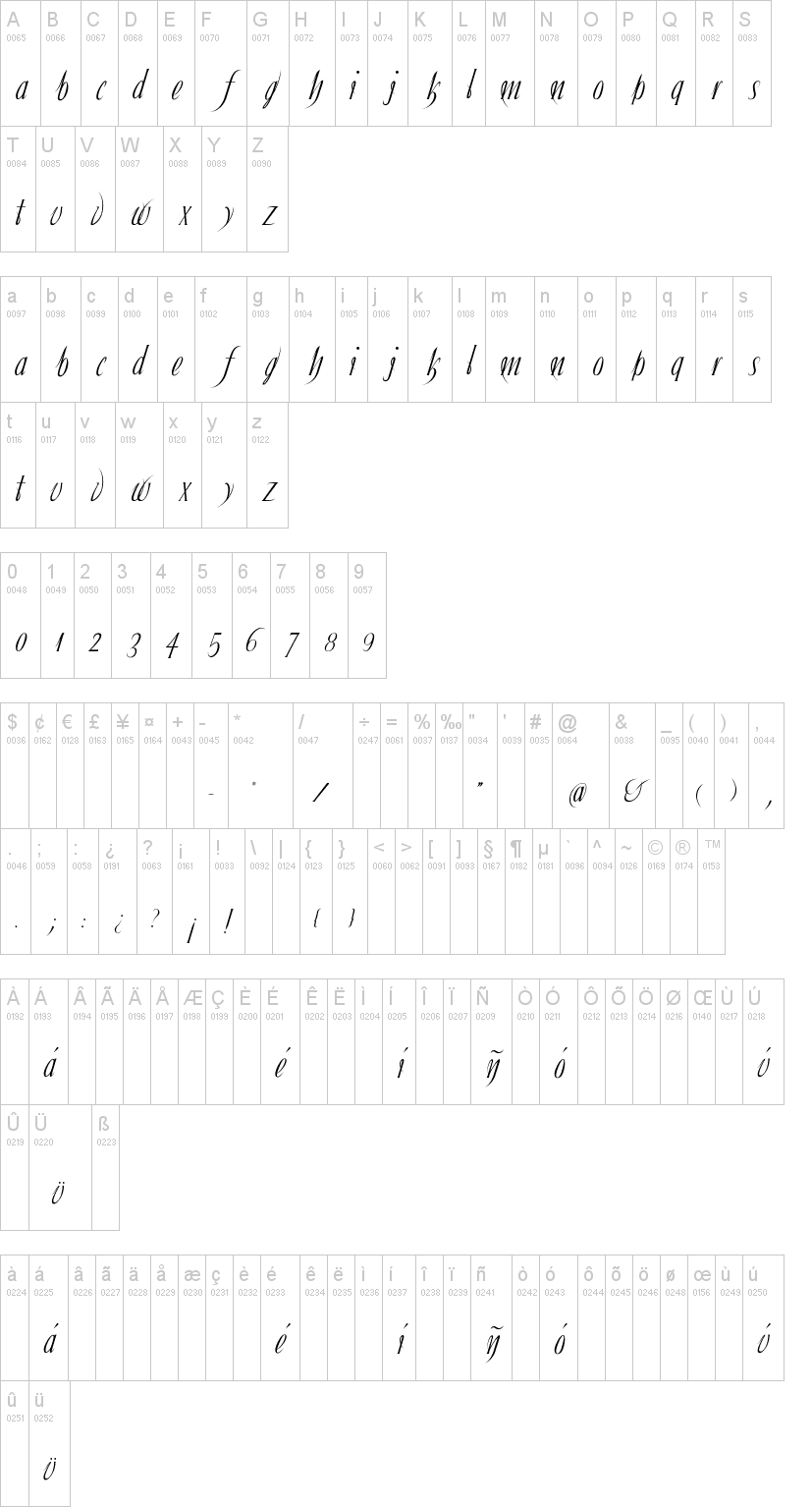
Note of the authorHecha a pulmon en la UBA catedra Longinotti, hija de Baskerville Italic, esta libre para el que quiera usarla. Y para el que crea que merece una donation.